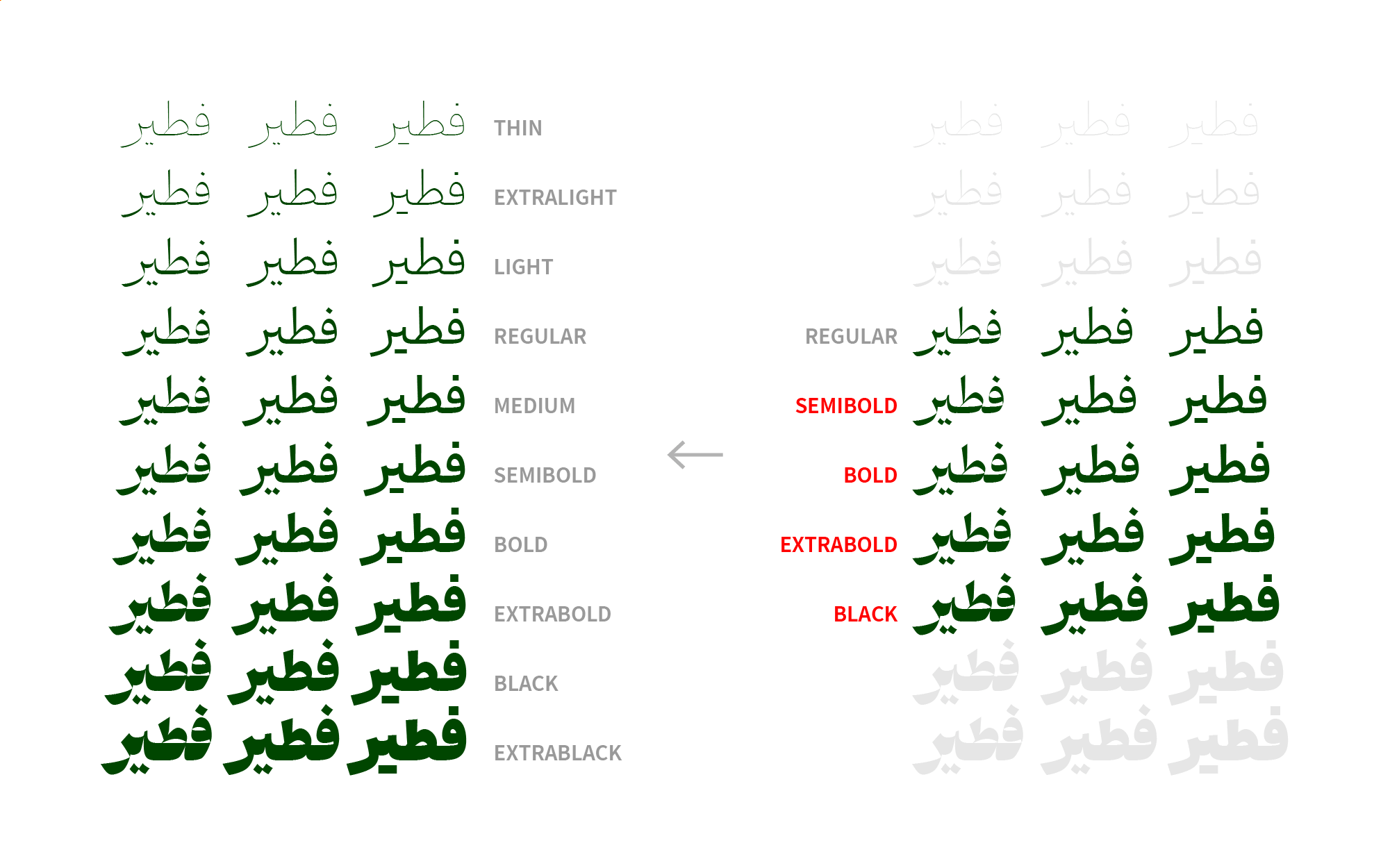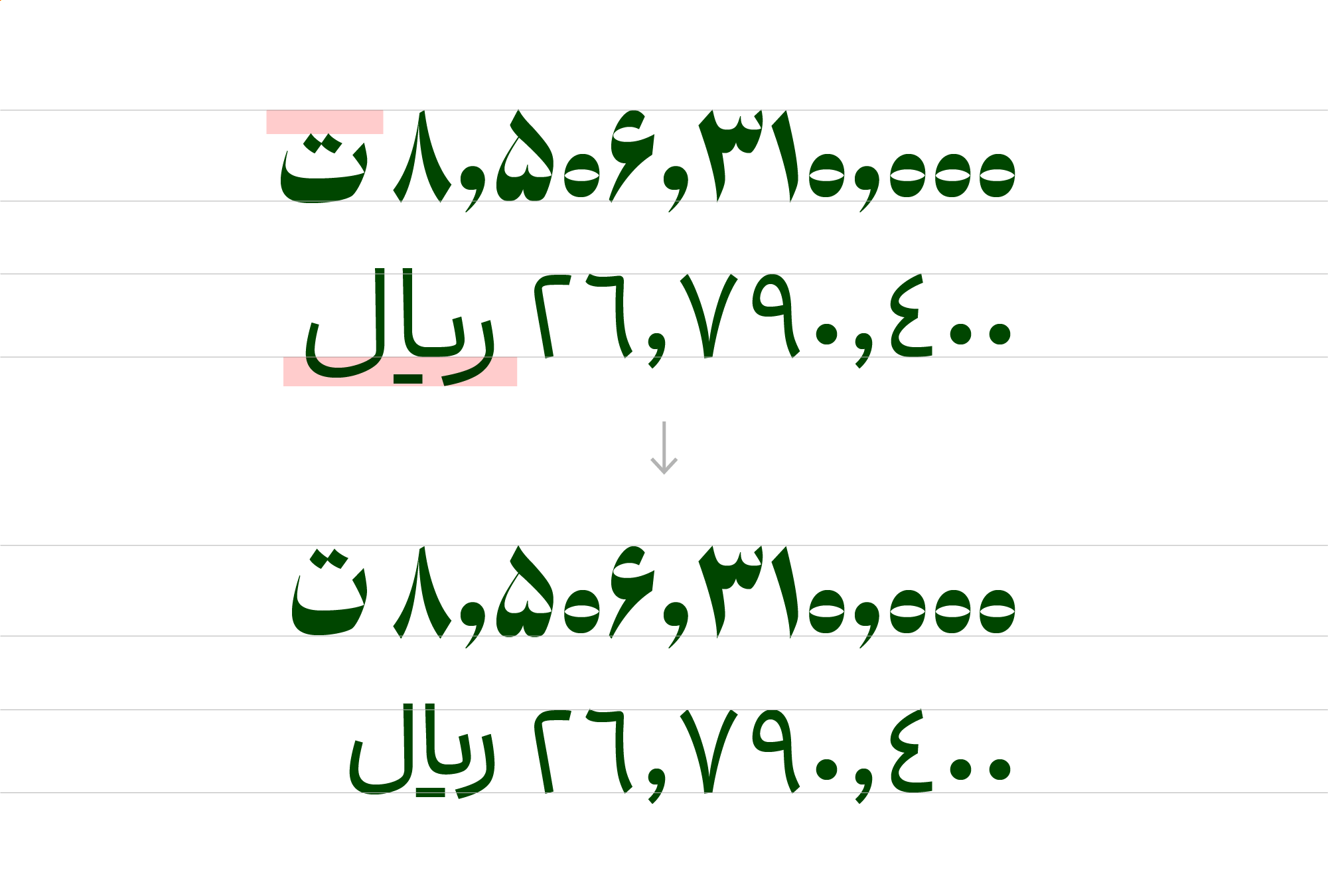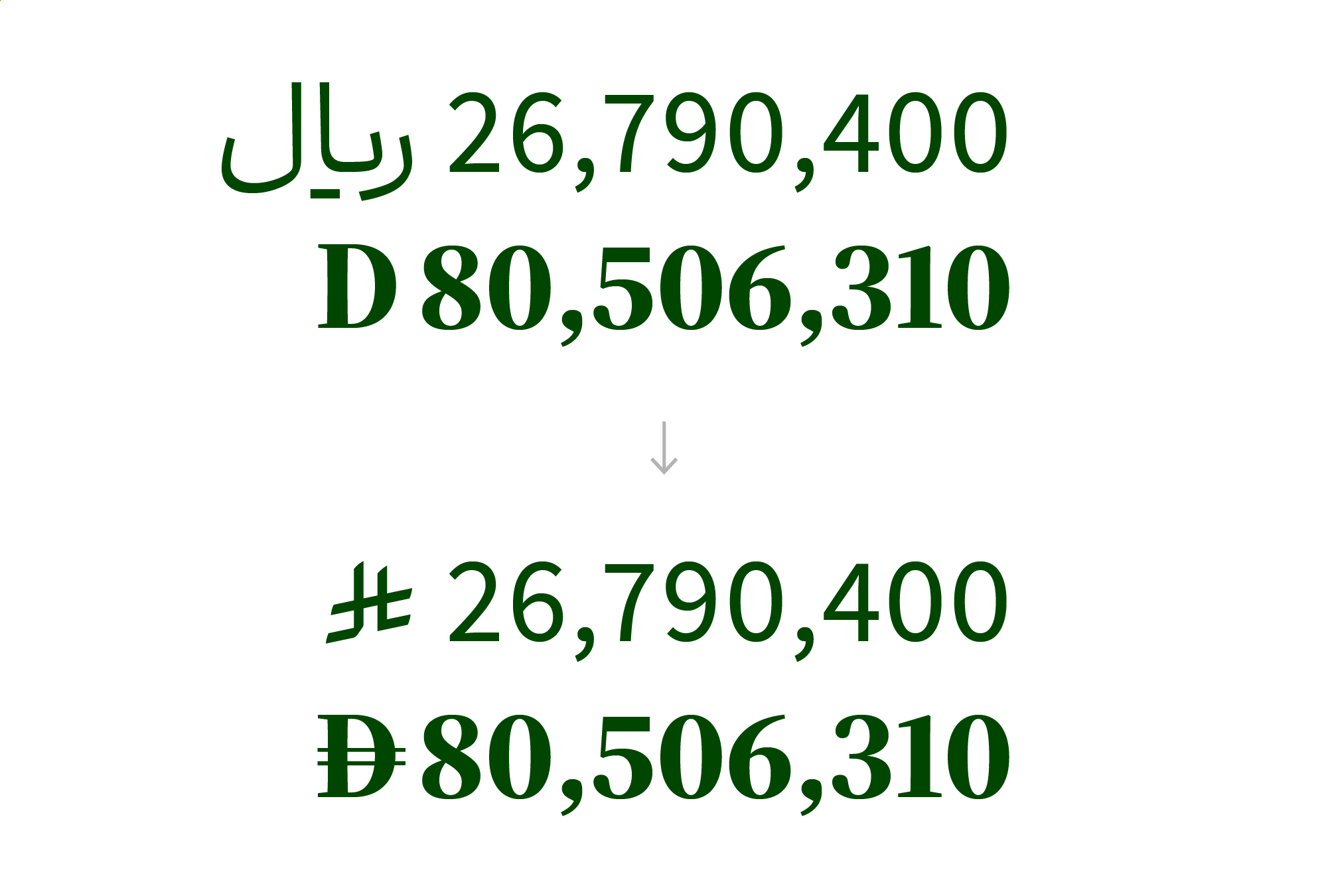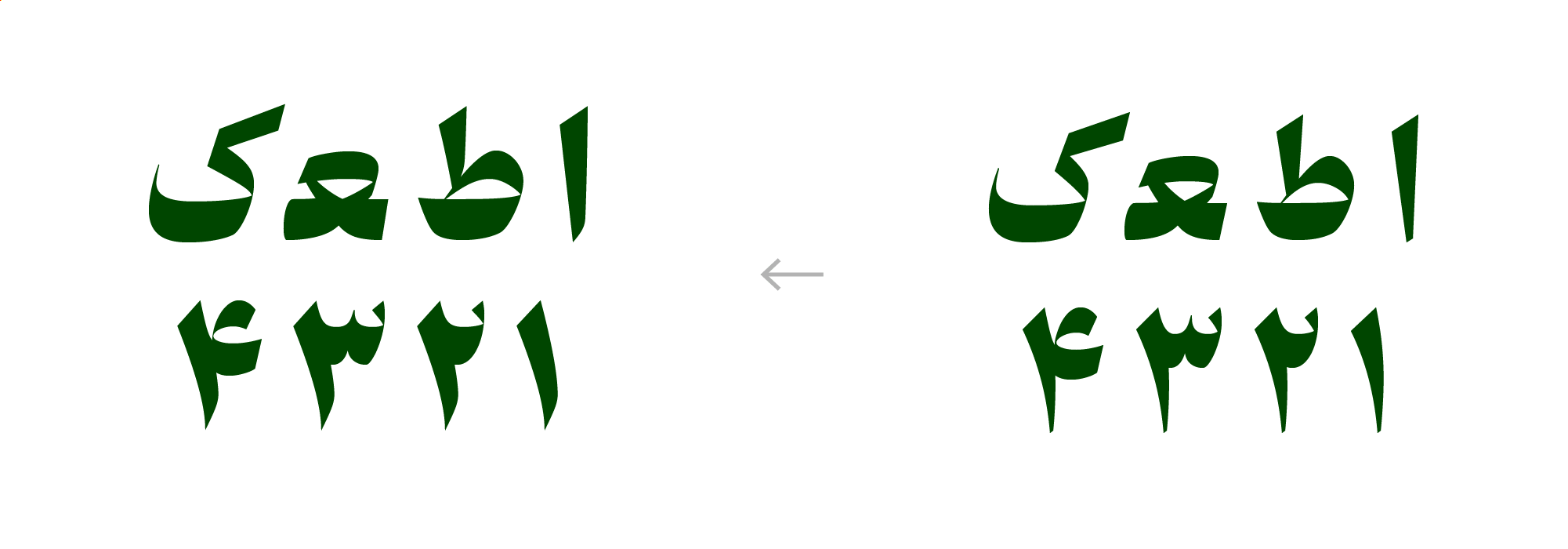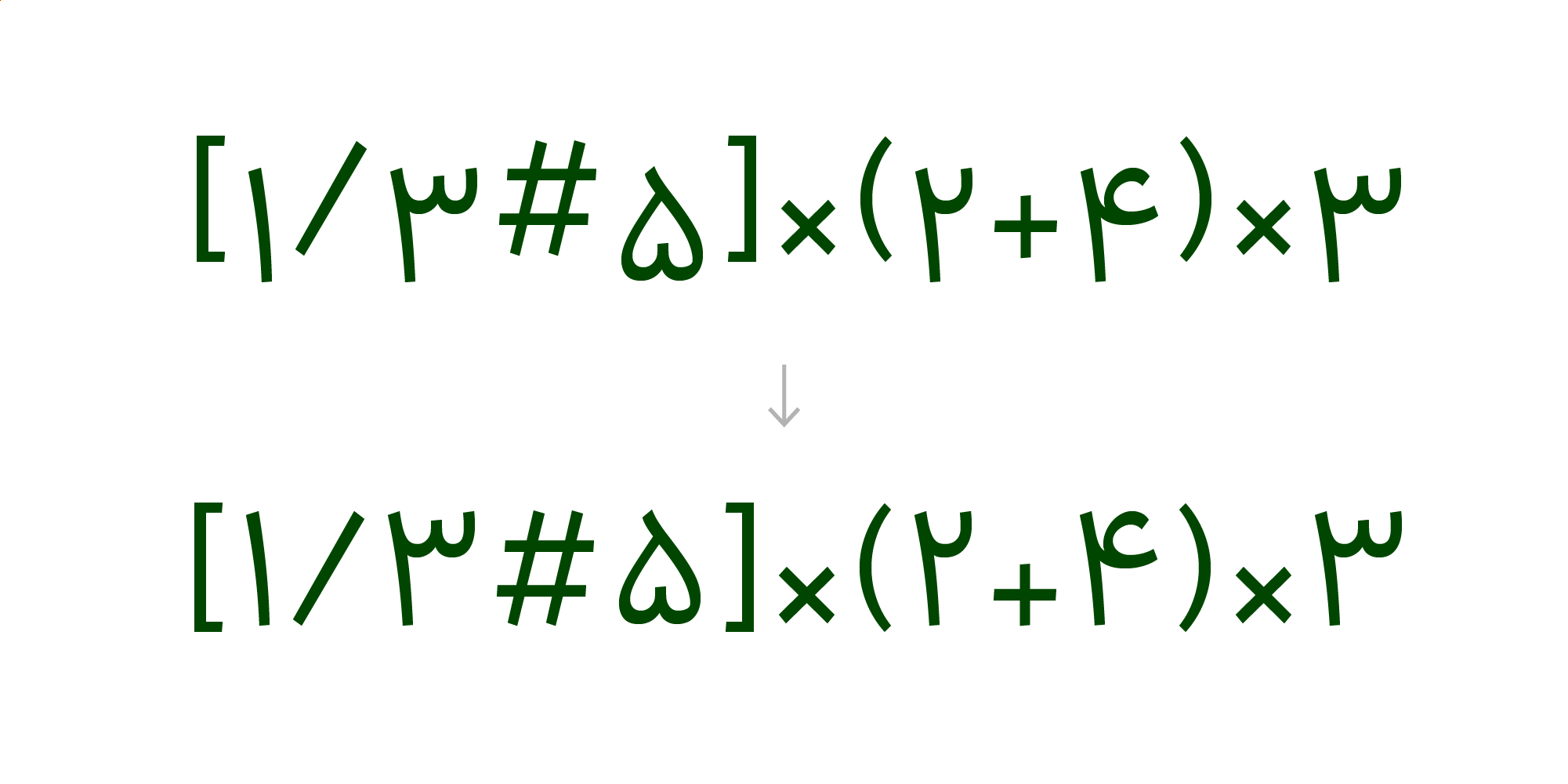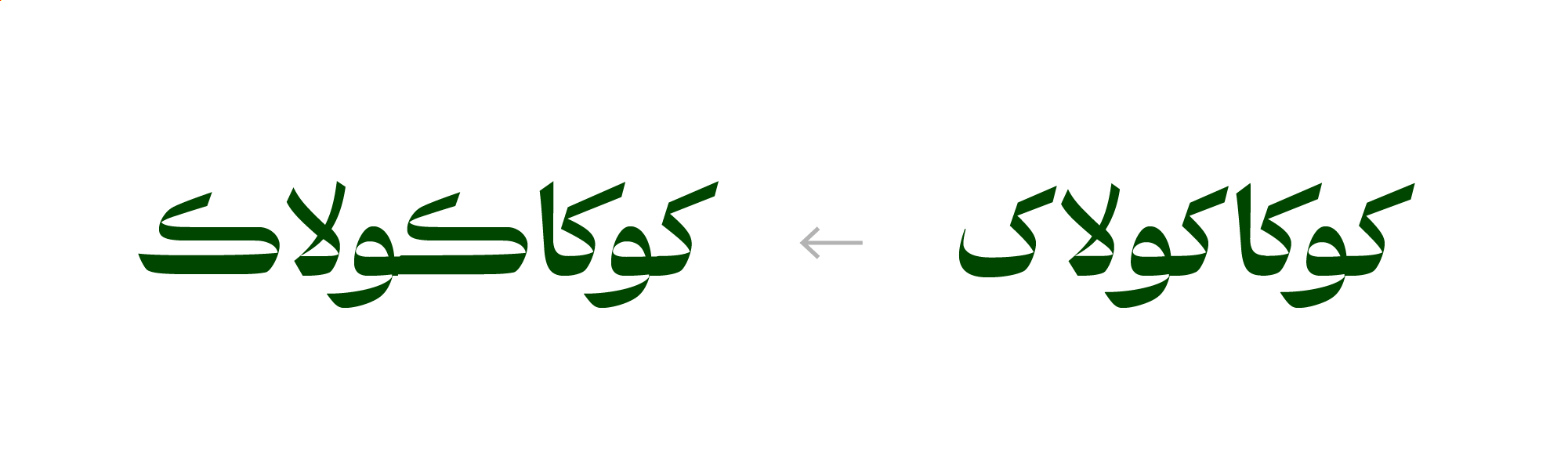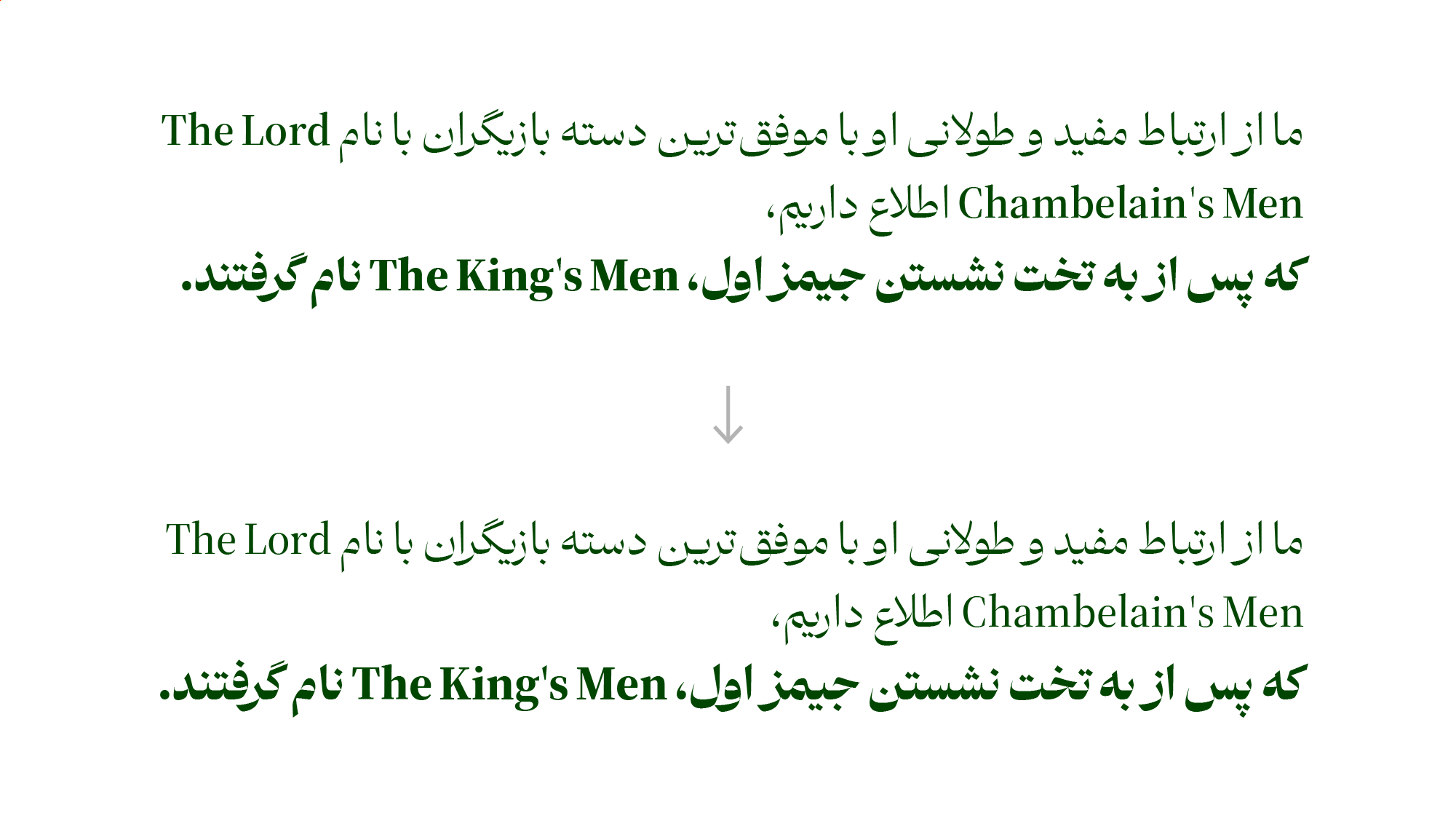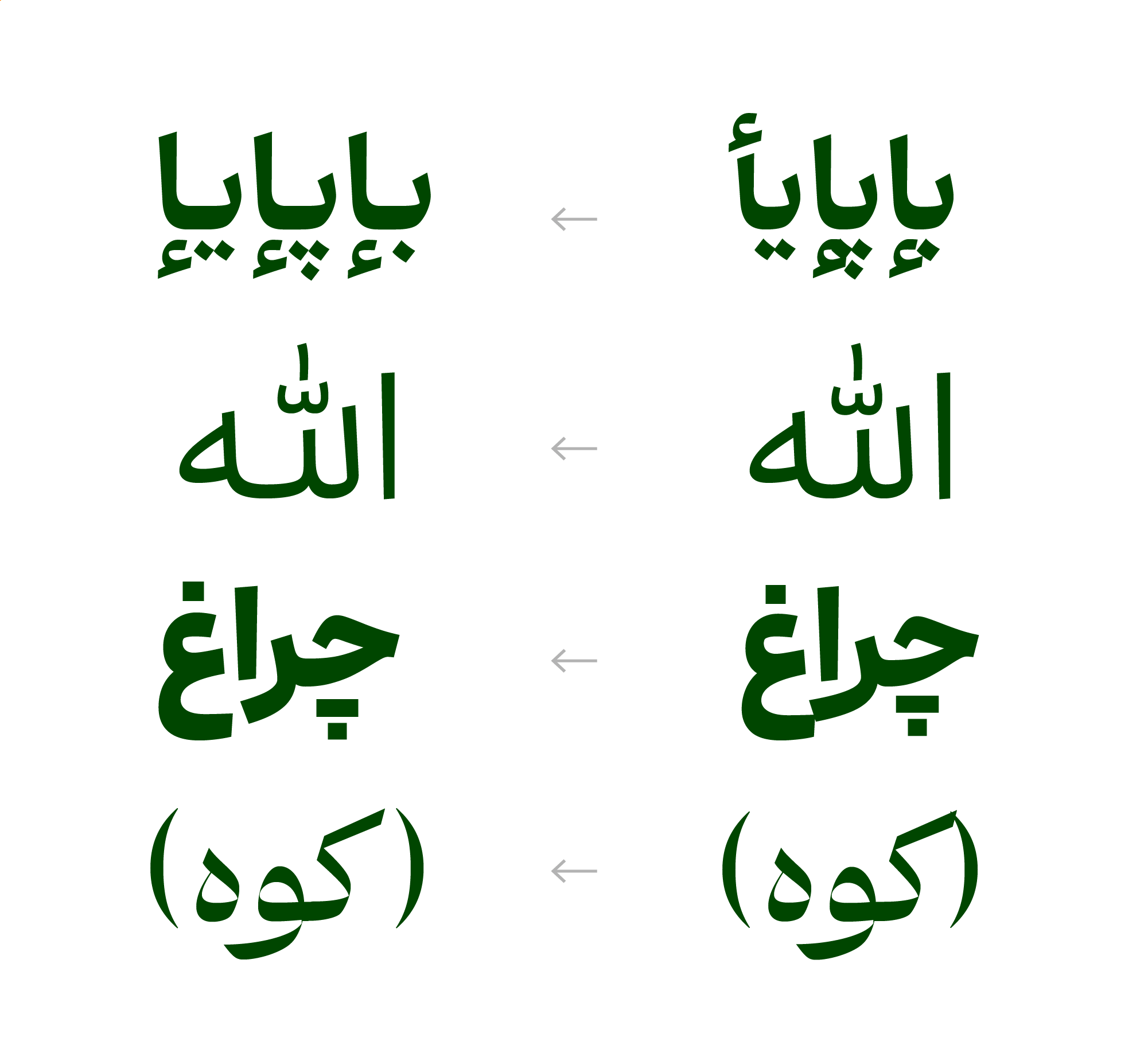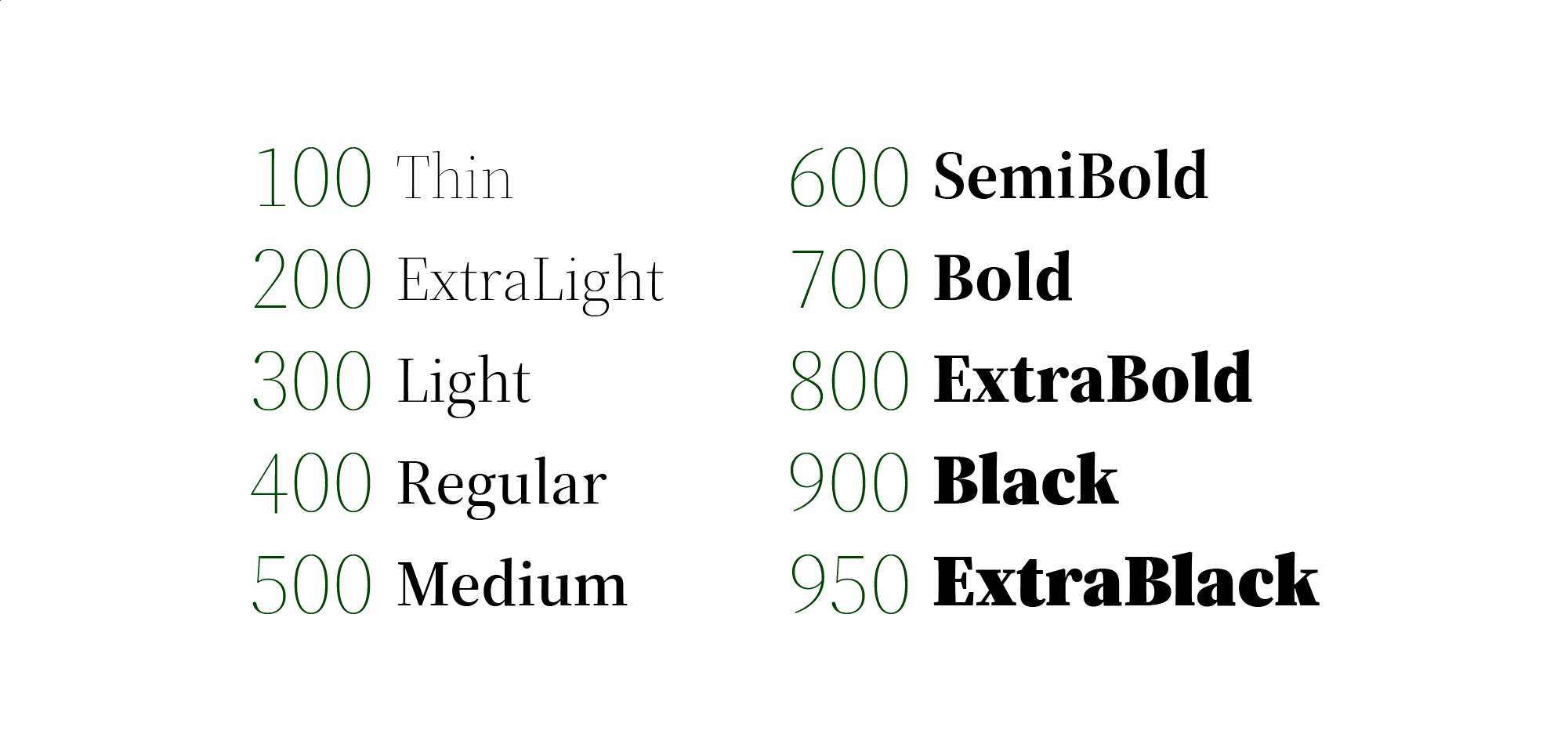
در نسخهی ۲ فونت ابَر چه تغییراتی میبینیم؟
- خانوادهی وزنی فونت کاملتر شد. حالا فونت ۳۰ عضو دارد (۱۰ وزن در ۳ سبک)، از Thin تا ExtraBlack.
- نامگذاری وزنها کمی تغییر کرد.
- نمادهای «ریال، تومان، ریال عربستان، درهم» برای فونت طراحی شد.
- فرم و فاصلهگذاری همهی کاراکترها بازبینی و اصلاح شدند.
- فرم حروف «ا ط ع ك ک ل» تغییر کرد.
- فرم اعداد «۱ ۲ ۳ ۴» تغییر کرد.
- با فعال کردن Stylistic Sets 4 تراز عمودی علائم ؟!٪؍٬٫/\⁄'#(){}[]|¦ با حروف همآهنگ میشود.
- «ک» سرکش کوتاه حذف شد. حالا در ترکیباتی که سرکش با حرف قبلی برخورد میکند، «ک» کشیده جایگزین میشود.
- ضخامت و اندازهی کاراکترهای لاتین بازبینی و اصلاح شد.
- مشکل برخورد الف زیرهمزه با نقطههای «ب پ ی ...» برطرف شد.
- «الله» کشیدهتر شد.
- برخورد «ر» با «ع ح» در ترکیباتی مثل چراغ اصلاح شد.
- مختصات وزنها در فونت وریبل اصلاح، و با حالت استاندارد همآهنگ شد.
- ارتفاع کاسهی «ع ح» در وزنهای سنگین کوتاهتر شد.
- حروف «ب ک ف س ص ق ل ن ی» در وزنهای سنگین کشیدهتر شدند.
- مشکل کشیده نشدن «ک» قبل از «الف و لام» حل شد.
- کنتراست ضخامت کاراکترها در نسخهی High بازبینی و اصلاح شد.
- ضخامت و جای Underline و Strikethrough تنظیم شد.
- به دلیل عدم یکپارچگی پلتفرمهای مختلف در ساپورت کرنینگ اعداد و ایجاد مشکلات، حذف شدند.